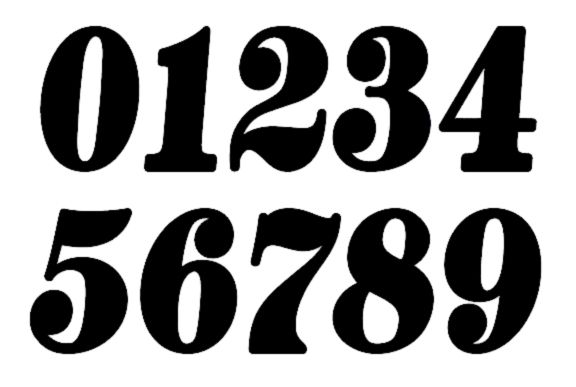
Foro de Tipografía que tipografía utiliza estos números el 29.04.2016 a las 16:05 por impresiondecamisetas · 2 comentarios Seguir este tema Dejar de seguir este tema 2 seguidores Buenas, lo primero presentarme, soy Gerardo y soy autodidacta en el tema de las tipografías, me gustan muchos las tipografías retro. Por eso mi consulta, alguien me podría decir que tipografía utiliza esta numeración. Muchas gracias Gerardo Comentar Me gusta
Busca tipografías del estilo de la Didot y Bodoni. En negrita y cursiva.